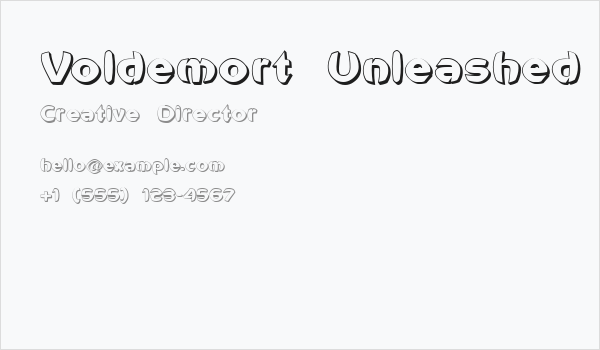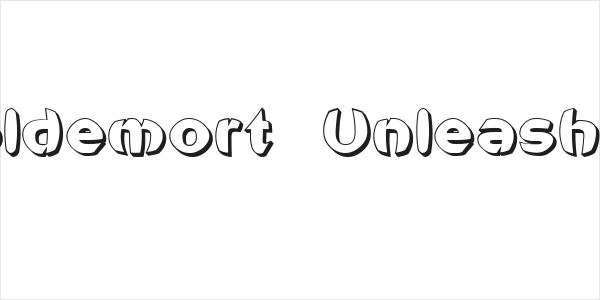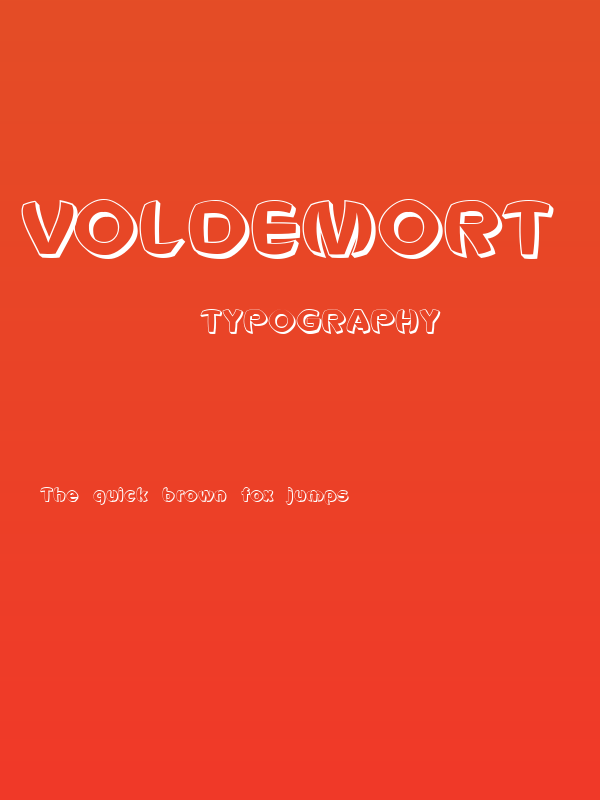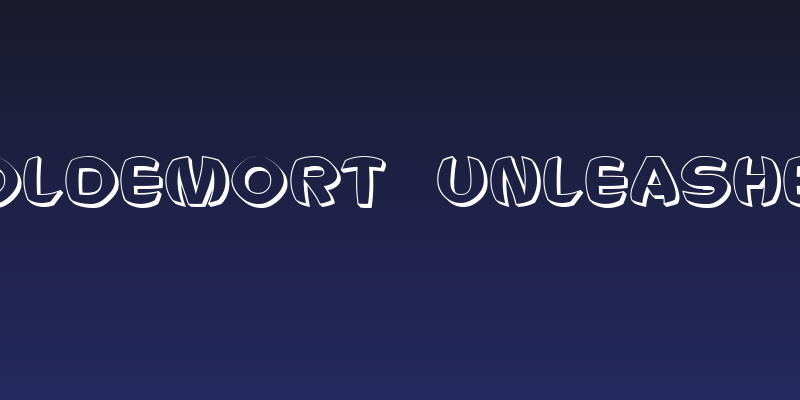
Voldemort Unleashed Font
| Gesamtstil | Playful, Dynamic |
| Vorgeschlagene Projekte | Ideal for comic book titles, children's book covers, playful branding, and eye-catching posters. |